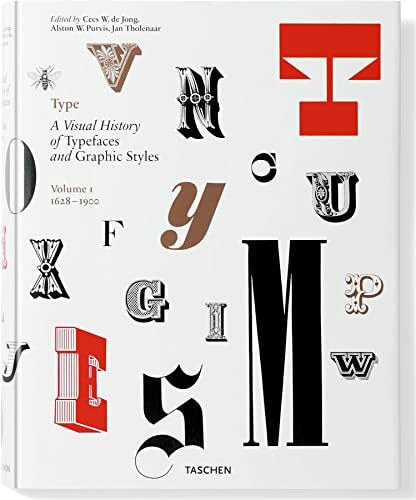
Type. A Visual History of Typefaces & Graphic Styles. 1628–1900: A Visual History of Typefaces and Graphic Styles, Vol. 1 (Type: A Visual History of Typefaces and Graphic Styles, Band 1)
"Type. A Visual History of Typefaces & Graphic Styles. 1628–1900: A Visual History of Typefaces and Graphic Styles, Vol. 1" von Alston W. Purvis ist ein umfassendes Werk, das die Entwicklung von Schriftarten und grafischen Stilen über mehrere Jahrhunderte hinweg untersucht. Der erste Band dieser Serie konzentriert sich auf den Zeitraum von 1628 bis 1900 und bietet einen detaillierten Überblick über die typografische Evolution in dieser Zeitspanne. Das Buch enthält eine Vielzahl von Abbildungen, die historische Schriften und Druckwerke präsentieren, und bietet Einblicke in die künstlerischen und technischen Fortschritte der Typografie. Es beleuchtet die Arbeit bedeutender Schriftgestalter und Drucker sowie den Einfluss gesellschaftlicher und technologischer Veränderungen auf die Entwicklung von Schriftstilen. Durch seine reichhaltige visuelle Dokumentation dient das Buch sowohl als Inspirationsquelle für Designer als auch als wertvolles Nachschlagewerk für Historiker und Typografie-Enthusiasten. Es zeigt, wie sich Ästhetik und Funktionalität im Bereich der Schriftgestaltung miteinander verbinden lassen und welche Rolle sie in der visuellen Kommunikation spielen.